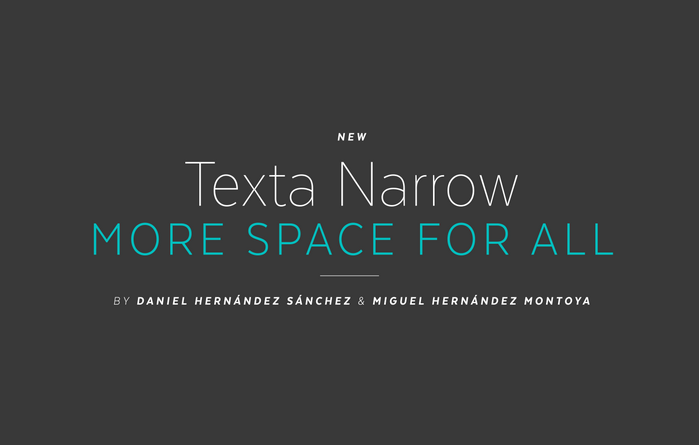
Texta Narrow Font
A Texta Narrow é uma tipografia aberta, moderna e transparente projetada para trabalhar perfeitamente tanto com textos formais quanto informais. Inspirada nos modelos humanistas do Edward Johnston até Adrian Frutiger, bem como no alfabeto gótico dos signatários de letras, a Texta Narrow é uma Sans-serif que se destaca pelo seu carácter racional e útil. Este design permite que as minúsculas “a”, “g” e “y” sejam substituídas por construções geométricas, resultando em maior versatilidade nas composições neutras. Uma versão alternativa ou Alt também foi incorporada, destinada a substituir a maioria das letras minúsculas com estruturas geométricas para aumentar ainda mais sua funcionalidade. Esta fonte é perfeitamente adequada para projetos onde se precisa de uma tipografia moderna e fácil de ler, tanto no formato de texto quanto em títulos. Com a Texta Narrow, você pode garantir um resultado elegante e claro, sem comprometer o aspecto visual da sua composição.